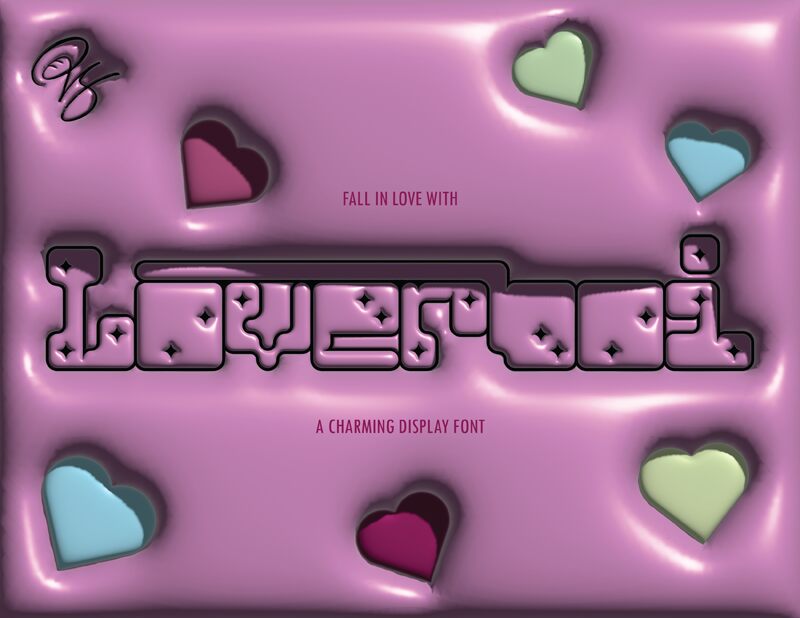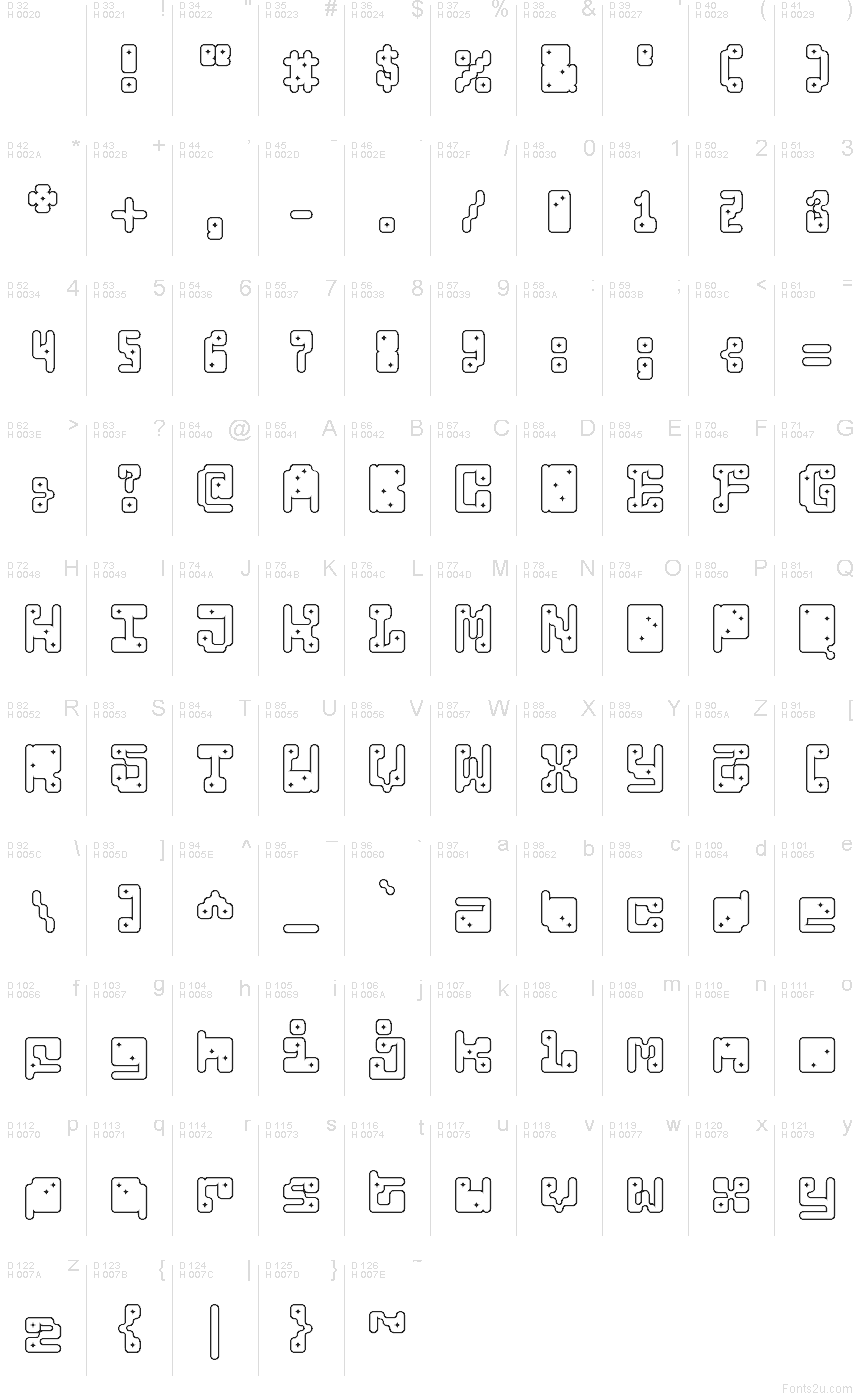
Loverboi-Regular
Loverboi, bezplatné groovy písmo typu outline z dielne Pendesal Studio, využíva bucľaté obdĺžnikové tvary a drobné hviezdicové detaily, vďaka čomu skvele evokuje popovú estetiku 70. rokov. Vďaka zaobleným rohom a nízkej, uvoľnenej siluete pôsobia znaky mäkko a graficky, nie strojene či formálne.
Vďaka tejto kombinácii je ideálne pre krátke nadpisy na obaloch albumov, módnych značkách, plagátoch na akcie, nálepkách alebo príspevkoch na sociálnych sieťach. Svoje uplatnenie nájde aj na obaloch produktov alebo v hlavičkách webov, kde výrazný obrys a akcenty v podobe hviezdičiek dokážu vytvoriť dokonalý štýl bez potreby ďalších ilustrácií.